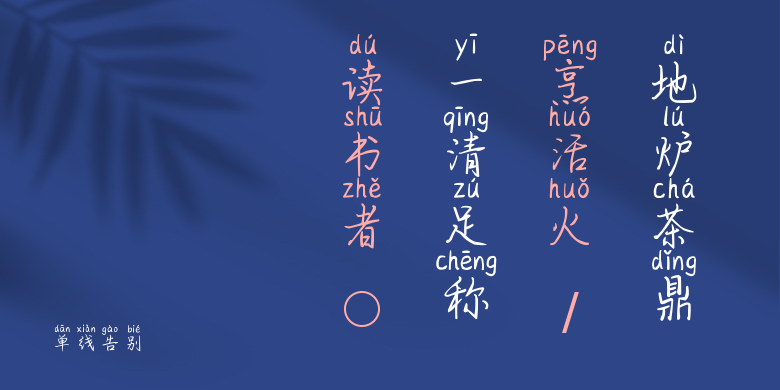
单线告别
单线告别,这款字体结构工整、笔画清晰,兼顾美观与易读性,适用于标题、正文、海报、包装、LOGO 等多种场景。字形优雅稳定,风格百搭耐看,适配日常排版与创意设计,让文字呈现更舒适、更具质感。单线告别一笔一画,皆是细节,以均衡的比例、流畅的线条打造舒适视觉体验,字形端正大气,风格简约现代。无论是商业设计、品牌宣传还是日常排版,都能轻松驾驭,让文字更有格调与力量。单线告别字体下载。